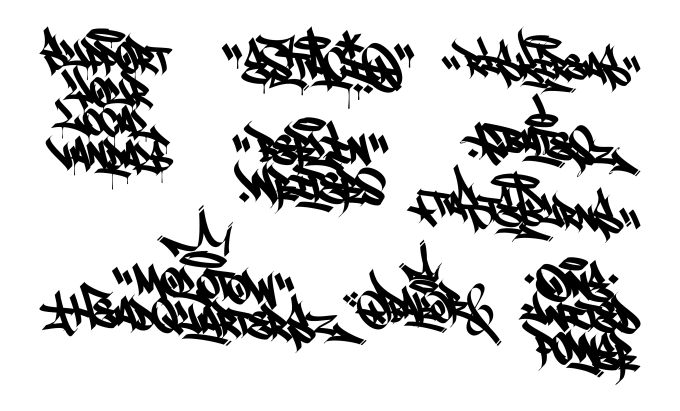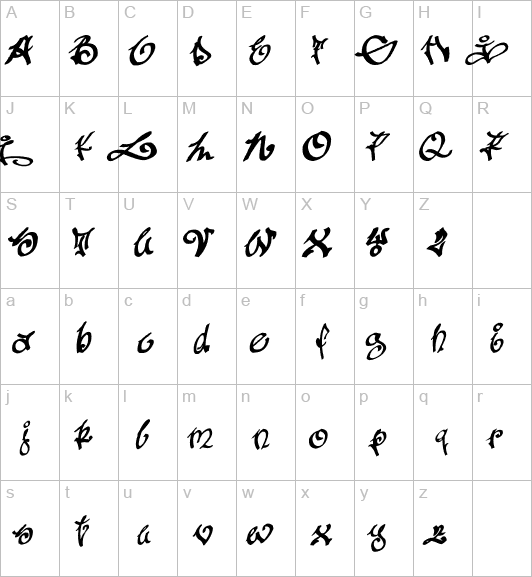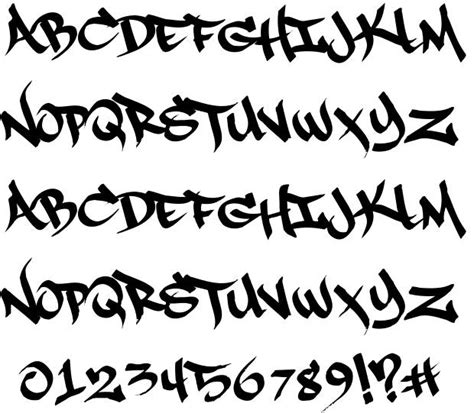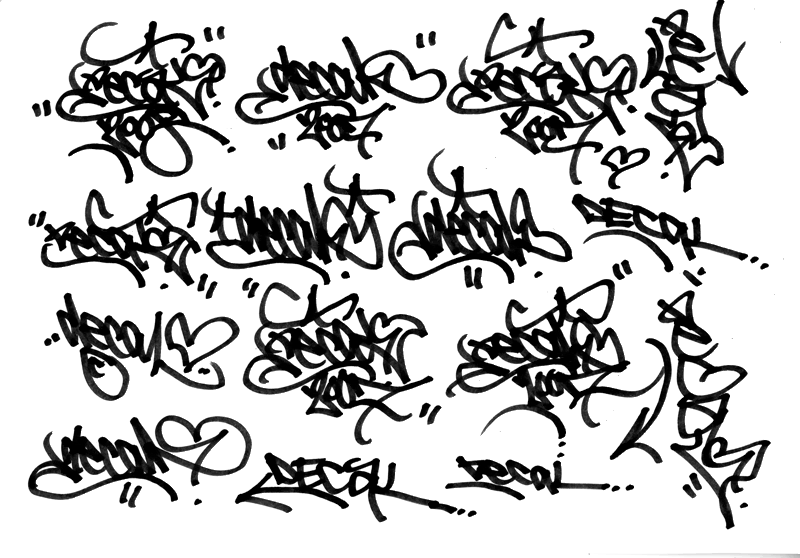
2012 г. Фото: © Лавпушер (Lovepusher) — граффити-райтер из Лондона, который рисует уже семнадцать лет. Он получил известность благодаря своему трехмерному стилю и надписи «Помни Иисуса» (Remember Jesus), а также двухмерным шрифтам, которые он создает под псевдонимом «Мегабайт» (Mbyte). В интервью блогу Source Synesthesia он рассказал, как увлекся граффити, почему начал писать «Помни Иисуса», поделился своими размышлениями о религии, духовности, рисовании, работе над стилем, граффити в Лондоне, а также значении эскизов, Интернета и журналов для граффити-культуры.
Увлечение граффити
Фото: Montana Cans Как-то раз, еще будучи школьником, англичанин случайно набрел на стену, на которой в нью-йоркском стиле была сделана надпись The Andersons. Огромные яркие буквы так впечатлили подростка, что он начал пытаться рисовать нечто похожее в школьных тетрадках. Когда будущий Лавпушер перешел в другую школу, оказалось, что один из его одноклассников увлекается граффити.
Помни Иисуса
2012 г. Фото: © Лавпушер«Я решил использовать свое умение рисовать, чтобы распространять положительные посылы.»
В течение восьми лет Лавпушер занимался нелегальным рисованиям. После этого, по его собственным словам, он попал в дурную компанию, не связанную с граффити, и понял что, если он ничего не изменит, его жизнь пойдет под откос. Он не знал, к кому обратиться и как именно изменить свою жизнь. И тогда он вспомнил, что родители и священники с детства говорили ему, что всегда нужно обращаться за помощью к Богу. Лавпушер так и поступил. «Я встал на колени и помолился. Я попросил Бога помочь мне найти выход. И прямо с этого момента моя жизнь изменилась к лучшему: в ней появились любовь, счастье, огромное количество прекрасных людей, с которыми я могу работать и у которых могу учиться. Меня настолько поразило, как быстро и круто изменилась моя жизнь, что я захотел по-своему отблагодарить Бога.
Лавпушер
2012 г. Фото: © Лавпушер«Нужно убрать из процесса рисования собственное эго и заменить его на какую-то важную мысль.»
С этого момента англичанин сменил свой тэг на Lovepusher: «Love (англ. ‘любовь’) — это Иисус и моя любовь к нему, а pusher (англ. ‘напористый человек’) — это я сам, то есть я этими словами распространяю любовь к Иисусу». Лавпушер говорит, что писать не собственное имя, а что-то другое для граффити-райтера странно, так как суть этой культуру заключается в многократном повторении собственного имени. «Чтобы отказаться от этого, нужно убрать из процесса рисования собственное эго и заменить его на какую-то важную идею или мысль», — говорит англичанин.
В 2003-2009-м годах английский райтер писал только «Помни Иисуса». «Я хотел напомнить себе и людям о том, что Христос может изменить нашу жизнь к лучшему», — говорит он.
С 2010-го года Лавпушер решил, что можно выражать ту же мысль аллегорически и начал экспериментировать. Так, на одной из стен он изобразил смерть в виде двух черепов, а возрождение в виде пирамиды, на вершине которой сияет золотой свет.
По словам Лавпушера, на протяжении всех этих лет, что он пишет «Помни Иисуса», он ни разу не сталкивался с людьми, которые бы плохо отзывались о его рисунках. Некоторые, правда, опасаются, что он — рьяный христианин, который будет убеждать их обратиться в его веру или рассказывать, что они попадут в ад, но это совершенно не так. Англичанин говорит, что все имеют право на собственное мнение и что он никогда не собирался никого ни в чем убеждать, а просто хотел своими работами донести до людей положительный посыл.
Религия
2010 г. Фото: © Лавпушер«Нельзя полагаться на искаженную картину, которую нам предлагают западные СМИ.»
«Как христианин, я горжусь своей верой, но в то же время я уважаю все прочие религии.
Как ни странно, меня очень интересует религиозное разнообразие мира и параллели, которые существует между христианством и другими религиями», — говорит Лавпушер. В 2011-м году он побывал в нескольких странах, чтобы больше узнать об их религии и культуре. Он съездил в Таиланд: там он читал буддийские тексты и посетил множество буддийских храмов. Затем он отправился в Египет, где ему рассказывали об исламе и о значении Корана в жизни мусульман. В Израиле он побывал у Стены плача и узнал очень много об иудаизме — одной из древнейших религий мира. «Мне кажется, очень важно, чтобы человек, перед тем как выносить какое-либо суждение или высказывать свое мнение относительно какой бы то ни было религии, изучил эту религию и «пережил» бы ее, а не полагался исключительно на искаженную картину, которую нам предлагают западные СМИ», — говорит Лавпушер.
«Мне кажется, граффити — один из наилучших способов выражать собственные взгляды.»
Некоторые считают, что граффити не тот вид искусства, который может говорить о духовности.
Однако английский райтер совершенно с этим не согласен: «Мне кажется, граффити — один из наилучших способов выражать собственные взгляды. Некоторым людям, возможно, не нравится, что религия и духовность появляются в граффити-работах, но вот, что я хочу спросить: почему в мире, переполненном изображениями обнаженных женщин, оружия, жестокости, иногда даже сатанизма одно-единственное позитивное высказывание заставляет людей чувствовать себя неуютно, так, как будто им что-то угрожает?»
Трехмерный стиль
2012 г. Фото: © Лавпушер«Я ничего не знал, но у меня было огромное желание учиться и создать свой собственный трехмерный стиль, и я занялся самообразованием.»
После восьми лет нелегального рисования Лавпушер заметил, что его стиль не сильно изменился. Ему это очень не понравилось, и он захотел попробовать что-то новое. В 2003-м году он увидел стену в пригороде Лондона, на которой Инса (Insa) сделал работу в стиле 3D. Этот рисунок произвел на английского райтера такое сильное впечатление, что он сразу же решил попробовать поработать с объемом.
10 лучших шрифтов для граффити
Для тех из вас, кто ищет стильный шрифт для создания аутентичного дизайна в уличном стиле, журналов, музыкальных плакатов или заголовков с эффектной типографикой, наша подборка из 10 лучших граффити-шрифтов поможет вам добавить смелый и уникальный вид. к вашей типографской работе.